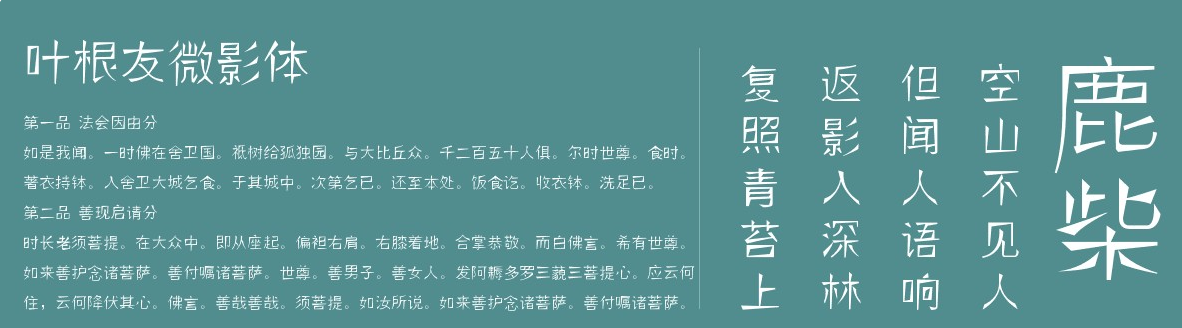
葉根友微影體字體是一款非常美觀的字體,整體十分的美觀優(yōu)秀,不僅在字形字體的設(shè)計(jì)上,打破了以前的設(shè)計(jì)觀念,給人一種全新的立體感覺,歡迎大家來綠色資源網(wǎng)下載體驗(yàn)。
葉根友微影體字體是一款全新的立體字體,該字體線條粗細(xì)不一,但整體結(jié)構(gòu)非常好看,并且字庫完整,能夠適用于包裝印刷、廣告設(shè)計(jì)、平面設(shè)計(jì)、書籍報紙等領(lǐng)域,在視覺效應(yīng)上跳出了傳統(tǒng)的平面模式,打造了一種全新的立體體驗(yàn)